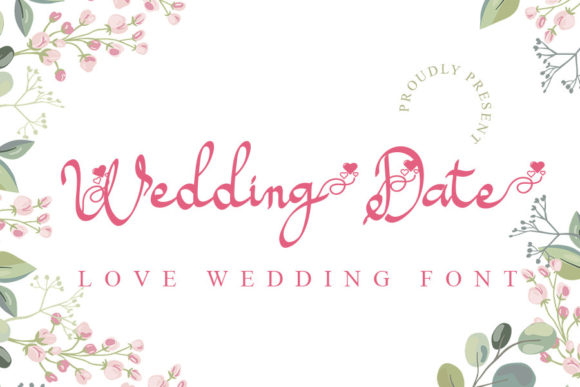
Creativefabrica Wedding Date Font
[Creativefabrica] Wedding Date Font
Wedding Date - шикарный, изысканный шрифт, излучающий утонченность и элегантность.
Стильные чередования и лигатуры делают этот шрифт идеальным для любого проекта.